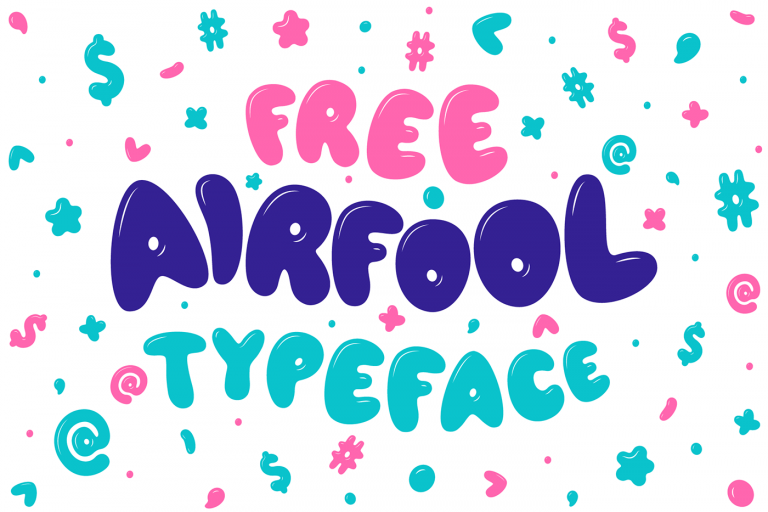
這款免費的英文字體,是由設計團隊 JUNNXY 提供的,非常活潑可愛的造型,有點像氣球一樣的字體,非常適合運用在生日、派對、節慶、兒童刊物上使用,這款 Alrfool 字型可以應用在個人或商業用途使用,設計師遇到女性客戶,套用這款字體就可以躺著收錢了 (騙肖ㄟ
不囉嗦,下面是這款字體在英文與數字還有符號的呈現範例